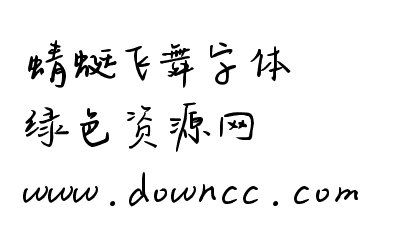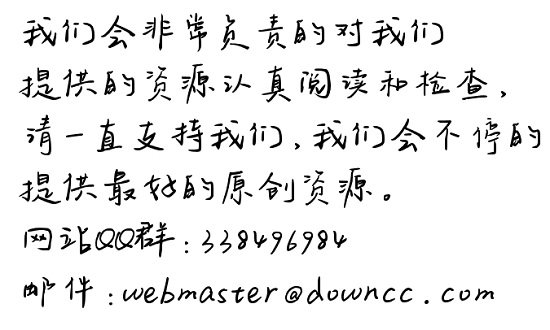
蜻蜓飛舞體帶給人安靜夏日午后的一股閑適心情,在這營(yíng)造的靜謐氛圍中,微游字跡濃淡相間,更顯生機(jī)盎然之態(tài),不一樣的閱讀體驗(yàn),只需在綠色資源網(wǎng)下載即可擁有!
本字庫是在國(guó)家標(biāo)準(zhǔn)簡(jiǎn)體字庫GB2312所包含6763漢字的基礎(chǔ)上,又增加了近200常用字,已經(jīng)覆蓋了大陸99.75%的漢字使用頻率,足以滿足日常需求。
在那些安靜的閑暇歲月中,沒有喧囂,沒有紛擾,有的只是蜻蜓飛舞般的輕盈和歡快。靜下心來,做一只快樂的小蜻蜓。
蜻蜓飛舞字體,采用了硬筆書法字體的風(fēng)格,給人清新雅致的活潑之氣,文字沒有矯揉造作之感,還原古色生香的獨(dú)特魅力,可以使用在藝術(shù)設(shè)計(jì)、包裝設(shè)計(jì)等多種產(chǎn)品中。